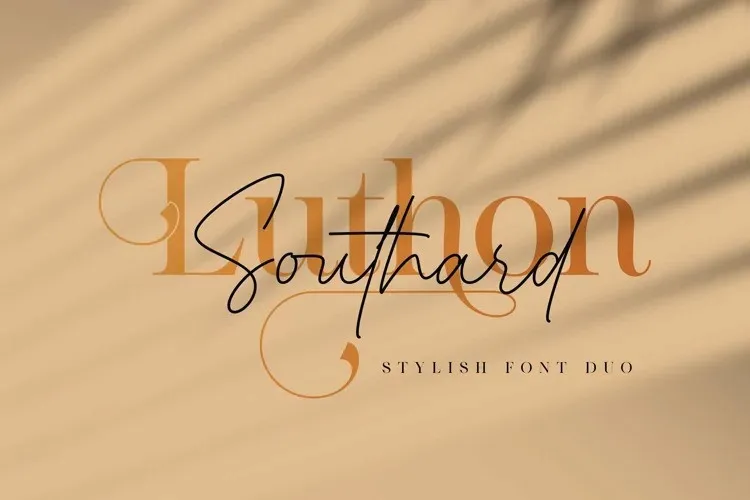
Luthon Southard Font Duo – Download Grátis
A Luthon Southard Font Duo é uma combinação elegante de serifada ideal para designers que buscam adicionar um toque sofisticado a suas criações digitais. Esta font seria perfeita para aplicativos de packaging, marcas e identidade visual, revistas, redes sociais, entre outros formatos visuais. Com seu design minimalista e sua delicada serifada, você pode tornar seus projetos ainda mais profissionais e atraentes. Seja um projeto de embalagem sofisticado ou uma postagem em rede social, a Luthon Southard Font Duo certamente ajudará a dar vida às suas ideias criativas, dando-lhes um charme único e diferenciado. Descubra a beleza desta fonte serifa e faça dela uma parte constante do seu trabalho de design.